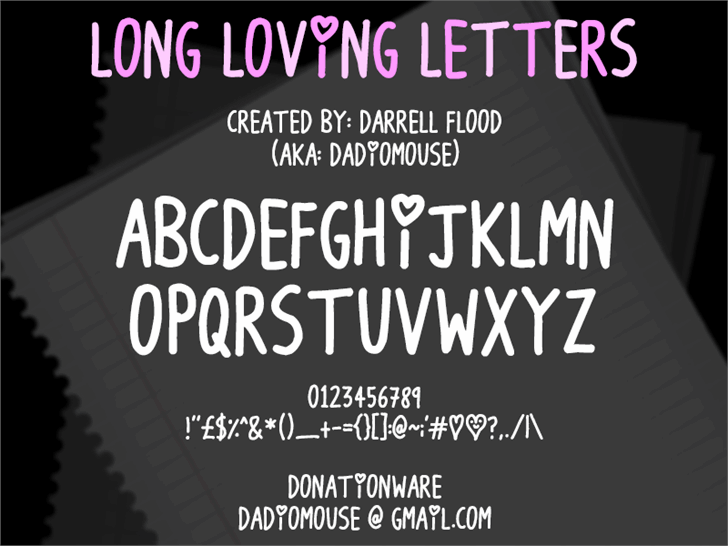
A fonte ‘Long Loving Letters’ é uma delicada fótn escrita a mão criada usando High Logic Scanahand por Darrell Flood. Seu design leva com carinho e amor, retratando sentimentos profundos e vínculos fortes entre duas pessoas. Inspirada na autêntica arte da escrita a mão, essa fonte é perfeita para criação de mensagens pessoais e emotivas. Ideal tanto para uso em aplicativos e websites quanto para impressão personalizada, ela traz um toque suave e romântico à sua produção digital. Hamilton, o designer, nos oferece uma opção única e emocional nesse catálogo de fontes escrita a mão, adequada para criações que buscam convidar seu público com um ar de leveza e profundidade emotiva.